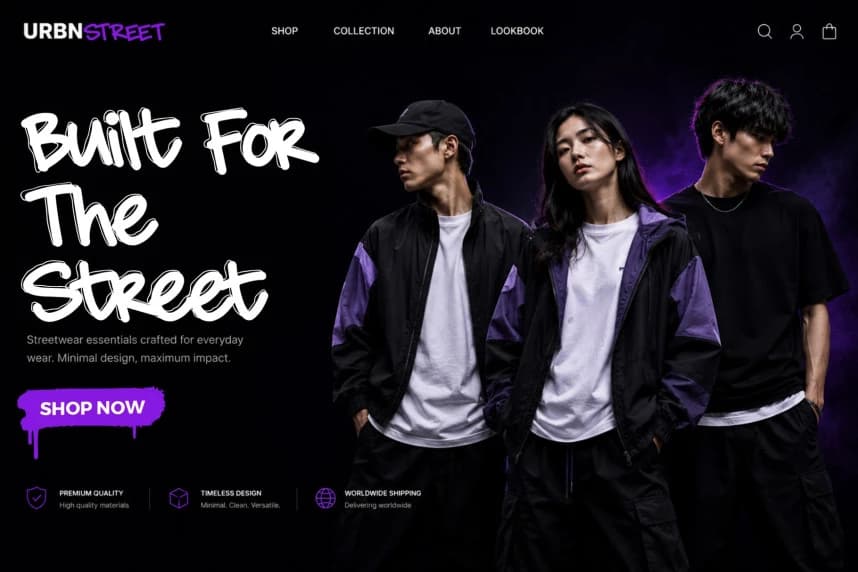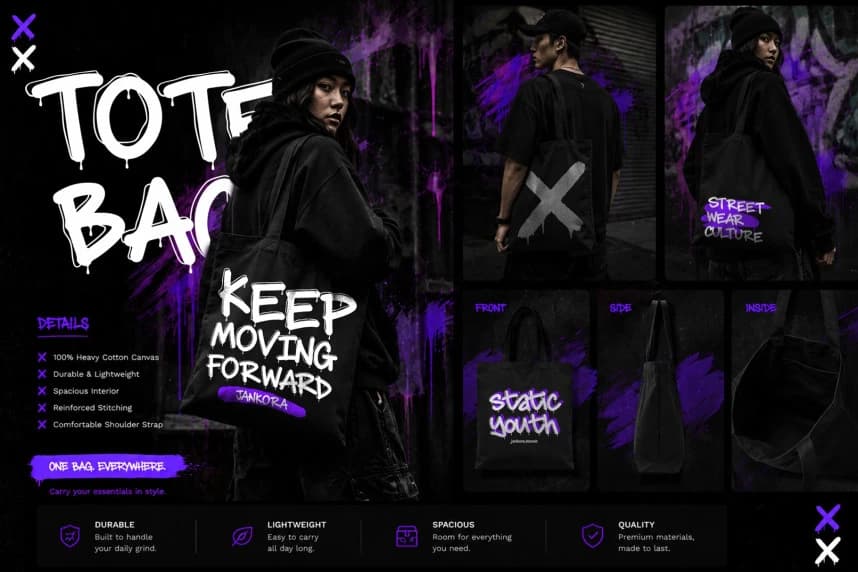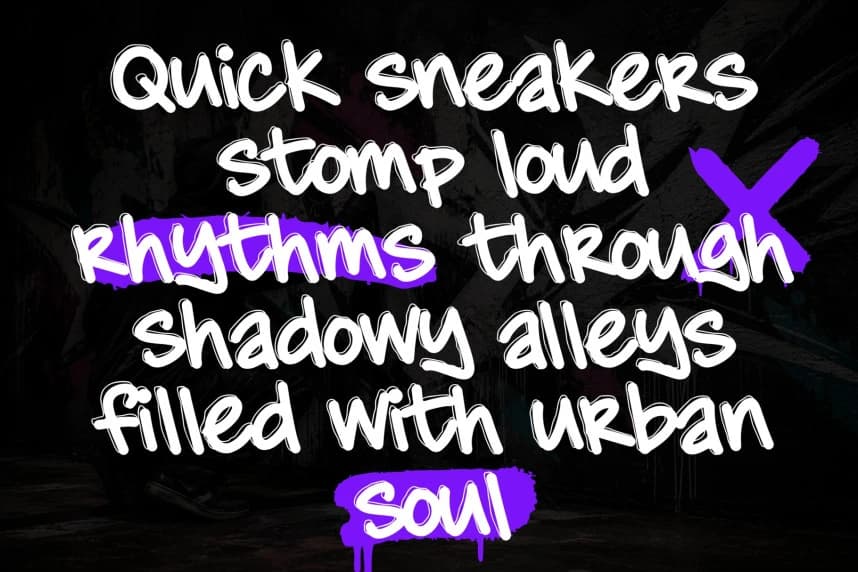
Jankora Street Yazı Tipi
Jankora Street Font, özgün kentsel sokak kültüründen, modern grafiti yazı stilinden, yeraltı hip hop estetiğinden ve cesur dekoratif tipografi trendlerinden ilham alan güçlü bir damlayan grafiti fontudur. İfade gücü yüksek monoline çizgileri ve damlayan grafiti detaylarıyla tasarlanmıştır.
Jankora Street Font, özgün şehir sokak kültüründen, modern grafiti yazı stili, yeraltı hip hop estetiğinden ve cesur dekoratif tipografi trendlerinden ilham alan güçlü bir damlayan grafiti yazı tipidir. İfadesi güçlü monoline çizgilerle ve damlayan grafiti detaylarıyla tasarlanmıştır.